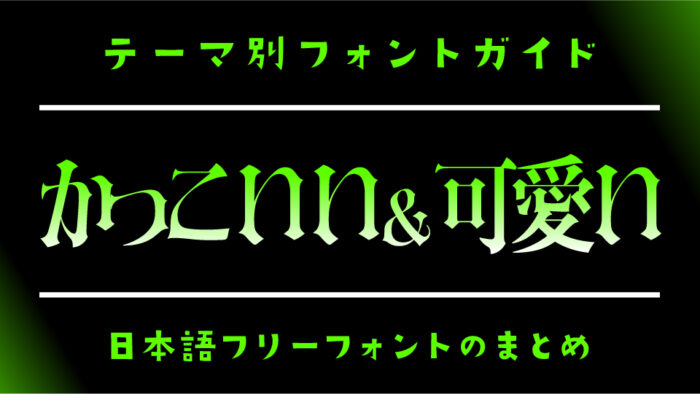
今回は、“かっこよさ”と“可愛さ”を両立した「ボーイッシュ」にぴったりなフリーフォントをご紹介します。
「かっこよくて可愛い」相反するようで実は相性抜群なテイストは、ガーリーすぎず、クールすぎない絶妙なバランスが魅力のフォントをまとめてみました。
ロゴや見出しタイトル、ポスター、SNS、サムネイルのデザインなどで「かわいいけど甘すぎない」「キメすぎないおしゃれ感」を演出したいときにぴったりのフォントばかりなので、ぜひ参考にしてみてください。
「かっこよくて可愛い(ボーイッシュ)」におすすめのフォントまとめ
以下のサンプル画像は本記事で紹介している一部ですが、「かっこよくて可愛らしい」そんなフォントデザインをまとめてみました。
黒薔薇ゴシック
黒薔薇ゴシックは、フリーフォントのゴシック体M+ FONTSから派生フォントとして、文字にトゲトゲの装飾が施されたデザインフォントです。
ウェイトが7種類用意されていますが、細いウェイトを使うことでボーイッシュな雰囲気が表現できます。
金畫字(キンカクジ)
金畫字(キンカクジ)フォントは、縦・横・斜(45°)の直線を主軸にデザインを展開し、四隅やハネや点・払いの表現に直角三角形で構成されているフォントです。
ハネの装飾がかわいい&かっこいい雰囲気を表現できている素敵なフォントです。
ゴチカクット
ゴチカクットフォントは、昭和〜平成初期頃に創業された電機機器メーカーなどのロゴで取り入れたようなスタイルで作られており、昭和レトロな印象もあるフォントです。
横浜ドット
横浜ドットフォントは、太めにデザインされた可愛らしい雰囲気を感じるピクセルフォントです。太めに作られているので、どっしりとしたカッコよさの中に、可愛さがあるフォントです。
セリフゴシック
AFSセリフゴシックフォントは、文字先にどっしりとしたセリフ装飾が付けられているデザインゴシック体のフォントです。お姫様っぽいエレガントさのあるカッコよくと可愛らしいフォントです。
略字超少明朝
略字超少明朝フォントは、一部の文字をステンシルのように改造されているのが特徴的で、ミリタリー的なカッコよさがあるデザインとなっています。
トレインOne
トレインOne(Train One)フォントは、文字のアウトラインを内側と外側の二重のラインで形成されているデザインのユニークなフォントです。
黒薔薇シンデレラ
黒薔薇シンデレラフォントは、長体ゴシック体をベースに薔薇のようにトゲトゲの装飾されているユニークなデザインフォントです。可愛げのあるクールなデザインがとても素敵です。
エイプリル
エイプリルゴシックフォント、角度を変形しているだけでもコミカルでポップな雰囲気がでてユニークなフォントです。
叛逆明朝
叛逆明朝(Hangyaku)フォントは、エレガントなクールさと、ゴスロリのような可愛さを持ち合わせているデザインフォントです。